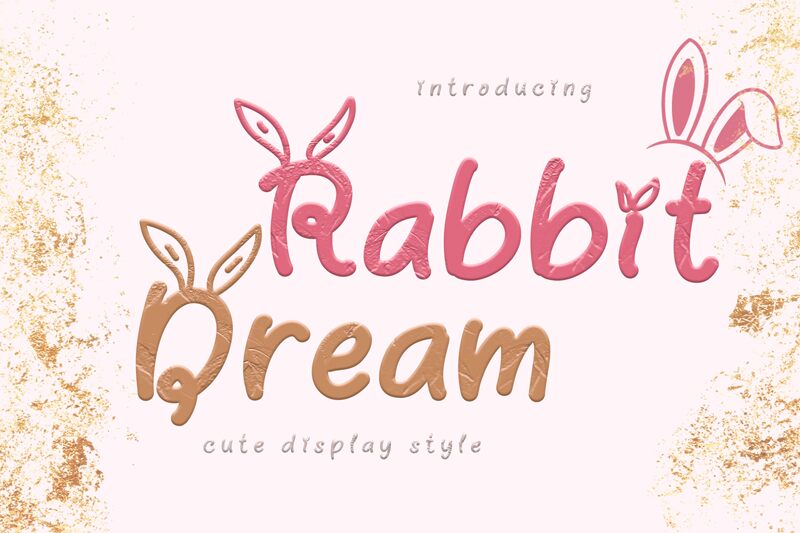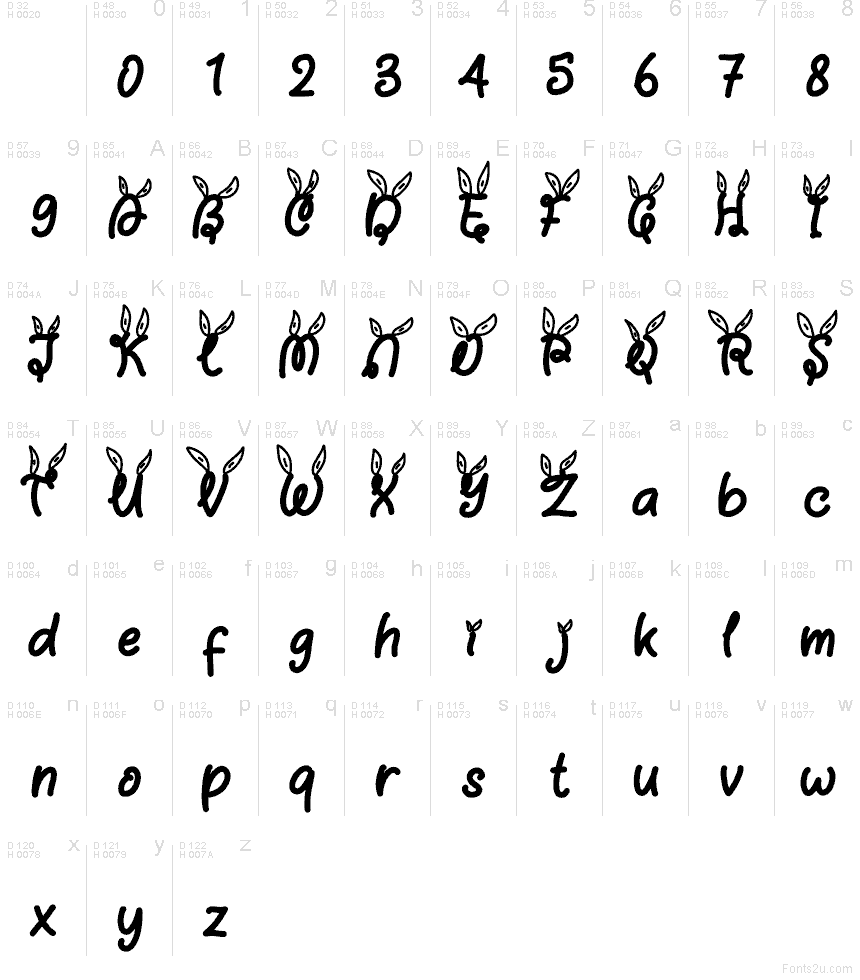
Rabbit Dream Demo
Rabbit Dream é uma fonte script gratuita para a Páscoa, com formas manuscritas arredondadas e detalhes de orelhas de coelho integrados na letra inicial. As letras mantêm um fluxo suave e casual, com curvas delicadas e um acabamento amigável que conecta todo o design ao tema festivo.
Rabbit Dream funciona perfeitamente para cartões de Páscoa, convites de primavera, embalagens de padaria, artesanato infantil e posts festivos nas redes sociais onde um toque temático é essencial. Esta fonte gratuita também se encaixa em cartazes de eventos e etiquetas sazonais, pois o motivo do coelho confere às letras um charme festivo imediato, sem a necessidade de decoração extra.